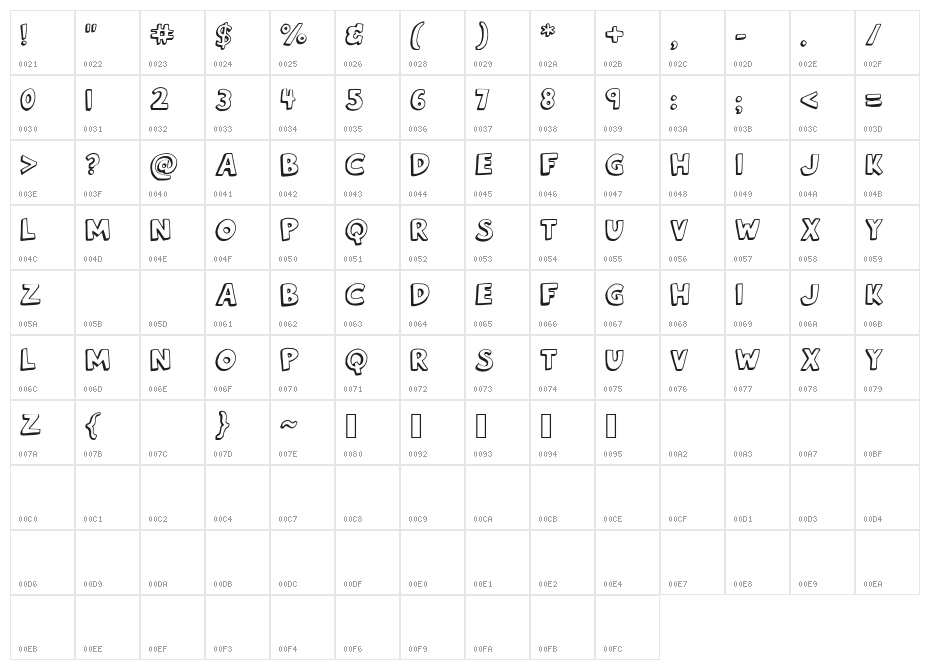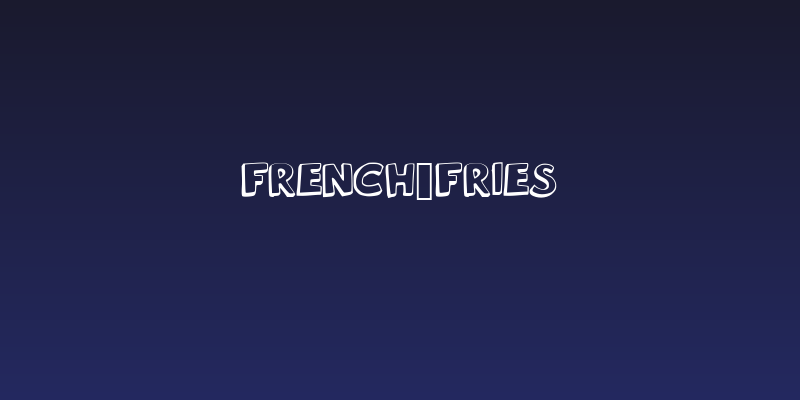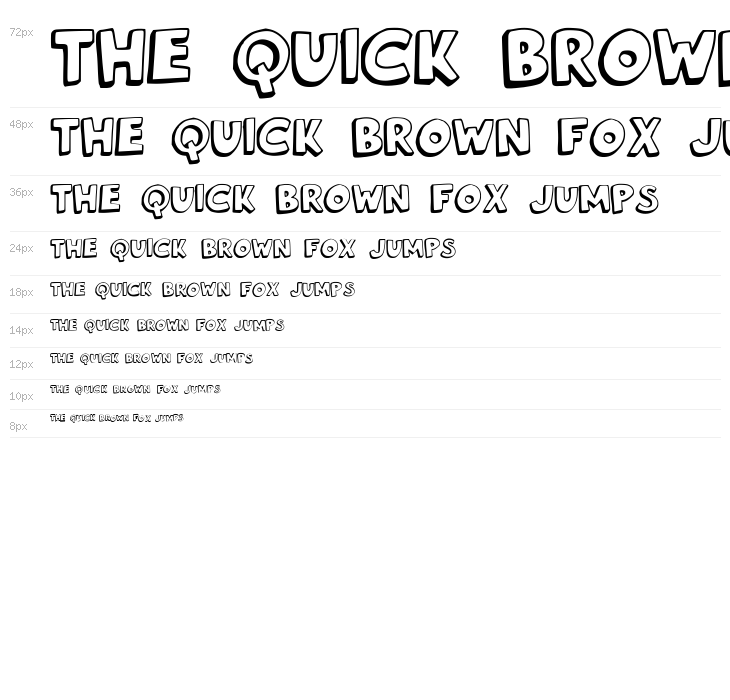
French_Fries Font
✎ Cartoon
Fonts by Geronimo
| Nombre | French_Fries |
| Categorías | Cartoon |
| Estilo general | Playful, Cartoonish |
| Proyectos propuestos | Perfect for children's books, comic strips, playful branding, party invitations, and any project needing a fun, lively touch. |
| Autor | Fonts by Geronimo |